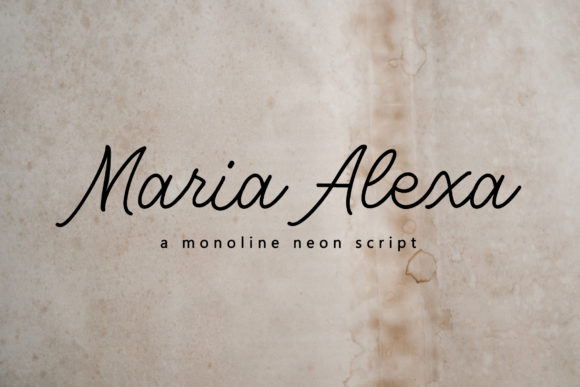
Maria Alexa
Maria Alexaのような高品質の素材をお探しの場合、このプレミアムパッケージはクリエイティブなプロジェクトに素晴らしい選択です。
POD(オンデマンド印刷)製品、結婚式の招待状、またはソーシャルメディアのグラフィックを作成している場合でも、Maria Alexaは理想的です。